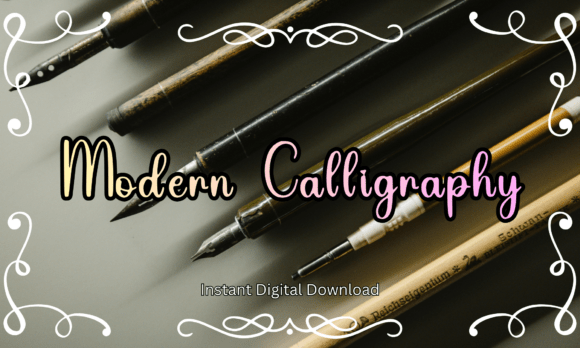
Modern Calligraphy
適切なデザイン要素を見つけるのは難しい場合がありますが、Modern Calligraphyは作品を即座に引き立てる優れたコレクションを提供します。
POD(オンデマンド印刷)製品、結婚式の招待状、またはソーシャルメディアのグラフィックを作成している場合でも、Modern Calligraphyは理想的です。